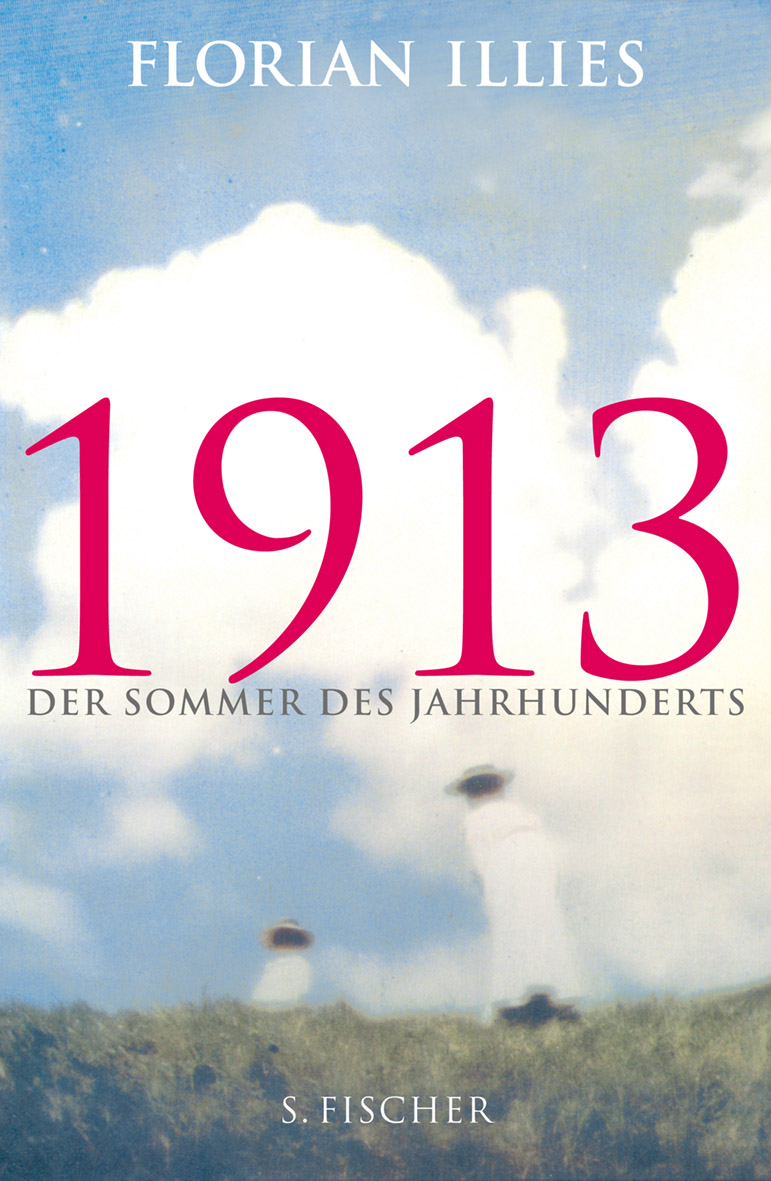
Florian Illies, 1913
ich bin auf der Suche nach der Schriftart des Covers von Florian Illies »1913«.
Ich habe schon »Whatthefont« probiert, aber dort wird mir die ITC Slimbach ausgegeben, die es nicht sein kann, wenn ich mir die 3 so ansehe.
Hat jemand vielleicht eine Idee?
alles auf dem cover ist aus dieser hier gesetzt:
ps: bei mir erkennt whatthefont das auch problemlos, gerade mal getestet. es gibt genau zwei treffer: trajan und eine gewisse caesario, eine digitalisierung derselben inschriften.
Bezüglich WhatTheFont würde mich dann interessieren, ob Du über URL gegangen bist oder es hochgeladen hast?! Offenbar gibt es ja dann unterschiedliche Ergebnisse?!
könnte es sein, dass das whatthefont-problem darin lag, dass du das komplette cover hochgeladen hast? zumindest bei mir gelingt es der software dann nicht, überhaupt irgendwelche buchstaben zu erkennen. ich habe daher für meinen test die zahlen ausgeschnitten und (unverändert) hochgeladen. dann kommt das oben genannte ergebnis. der autorname oder andere textteile hätten vermutlich auch funktioniert. ob du von deiner festplatte oder über eine url auf den whatthefont-server hochlädst, dürfte am ergebnis nichts ändern. die bieten nur beides an, weil das eine manchmal bequemer ist als das andere.
Bei WhatTheFont und WhatFontIs ist es immer am besten, man hat eine Zeile des fraglichen Textes möglichst in dunkler Schrift auf möglichst neutralem einfarbigen (vorzugsweise weißen) Hintergrund. Ist hinter dem Text irgendeine Bildinformation, oder ist es gar ein komplettes Bild, das irgendwo Text drauf hat. Das geht dann zu 100% in die Hose.
könnte es sein, dass das whatthefont-problem darin lag, dass du das komplette cover hochgeladen hast? zumindest bei mir gelingt es der software dann nicht, überhaupt irgendwelche buchstaben zu erkennen.